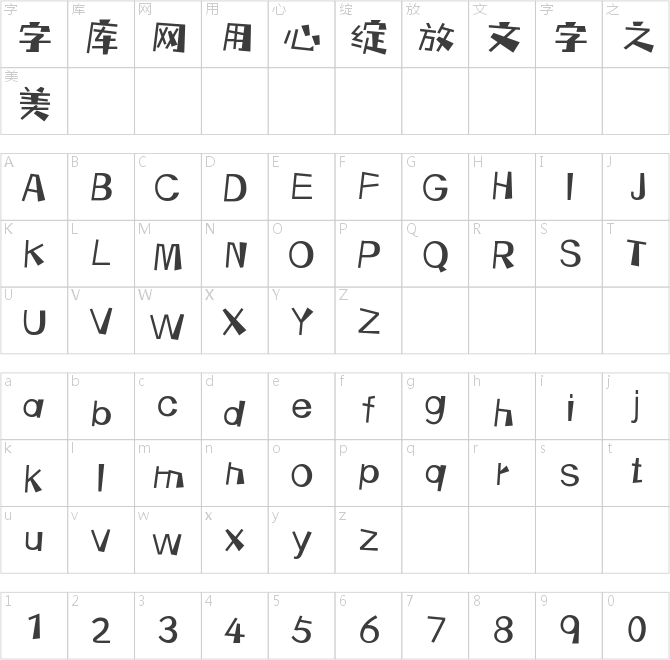
三極楓林簡體 粗 詳情頁
字體名稱: 三極楓林簡體
三極楓林簡體 粗
三極楓林簡體 粗 字體字庫是一款讓人賞心悅目、百看不厭的中文字體,適合各類廣告和產(chǎn)品包裝設(shè)計(jì)應(yīng)用,字體大小2.99MB,格式為ttf字體,上傳用戶是三極字庫,作者/版權(quán)方為三極字庫